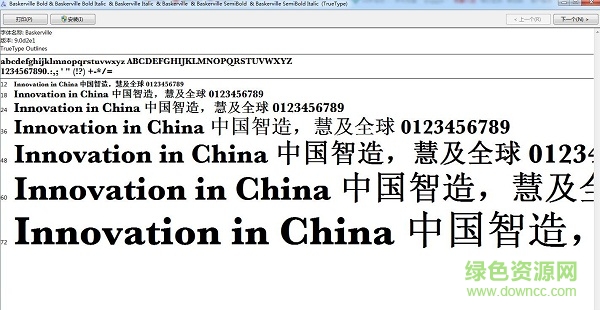
baskerville semibold
baskerville semibold字體是一款流暢灑脫的英文字體,線條工整,字身緊湊,結(jié)構(gòu)嚴(yán)謹(jǐn),字體可以用作宣傳排版用字以及廣告字體,喜歡的朋友快來下載吧!
英文襯線字體分類
1.根據(jù)襯線變化可以分成三類:具有特定曲線的襯線為“支架襯線體”,連接處為細(xì)直線的是“發(fā)絲襯線體”,厚粗四角形的“板狀襯線體”。
2.更加字形來分,襯線體可以分成兩類:類似手寫的襯線體叫“舊體”,比例工整,沒有手寫痕跡的襯線體叫“現(xiàn)代體”。